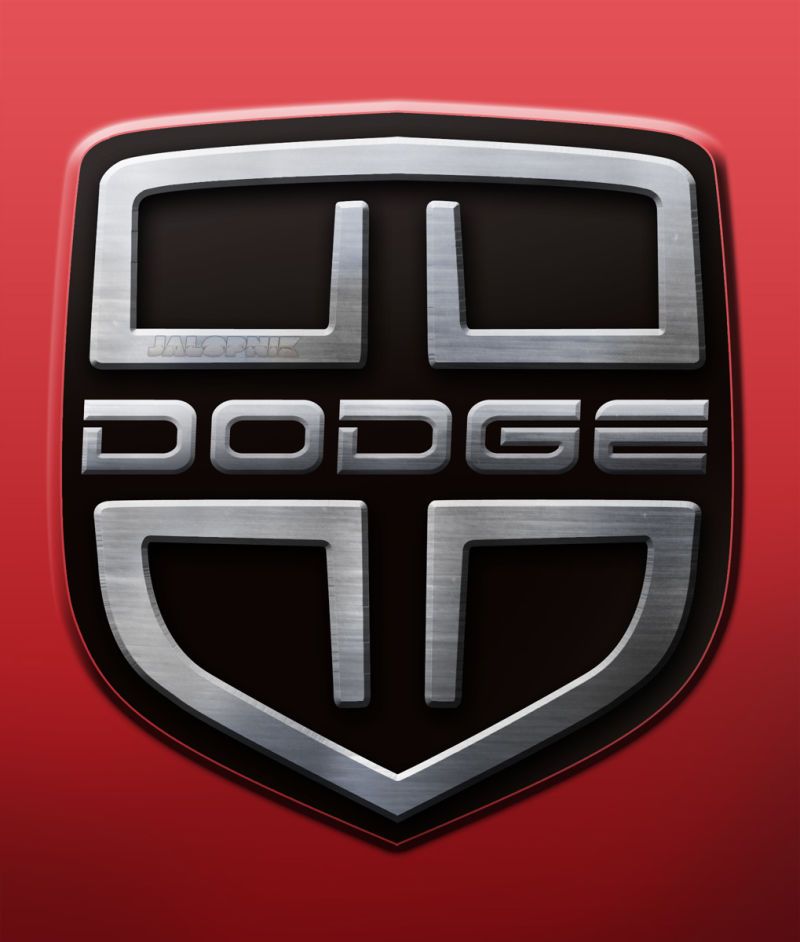
A ver si alguien reconoce esta fuente. Se parece a la de Terminator o a la Mechwar pero ya he comprobado que no es. He usado whatthefont y tal y no da resultado. Temo que sea una fuente gratuita de esas de dafont y me vaya a costar la vida localizarla (y eso si la localizo).
En todo caso la fuente ya ha sido identificada, es una Dodger, supongo que porque copia a las del logo de Dodge
TRUCO: Para obtener mayores y / o diferentes resultados pon mas o menos letras en la imagen a buscar, es curioso que da resultados diferentes, a veces repetidos.
Es muy parecida a la Handel Gothic negrita cursiva, a lo mejor te resulta mas facil modificarla si es solo para pocas palabras
Aqui lo identifica como Transpond